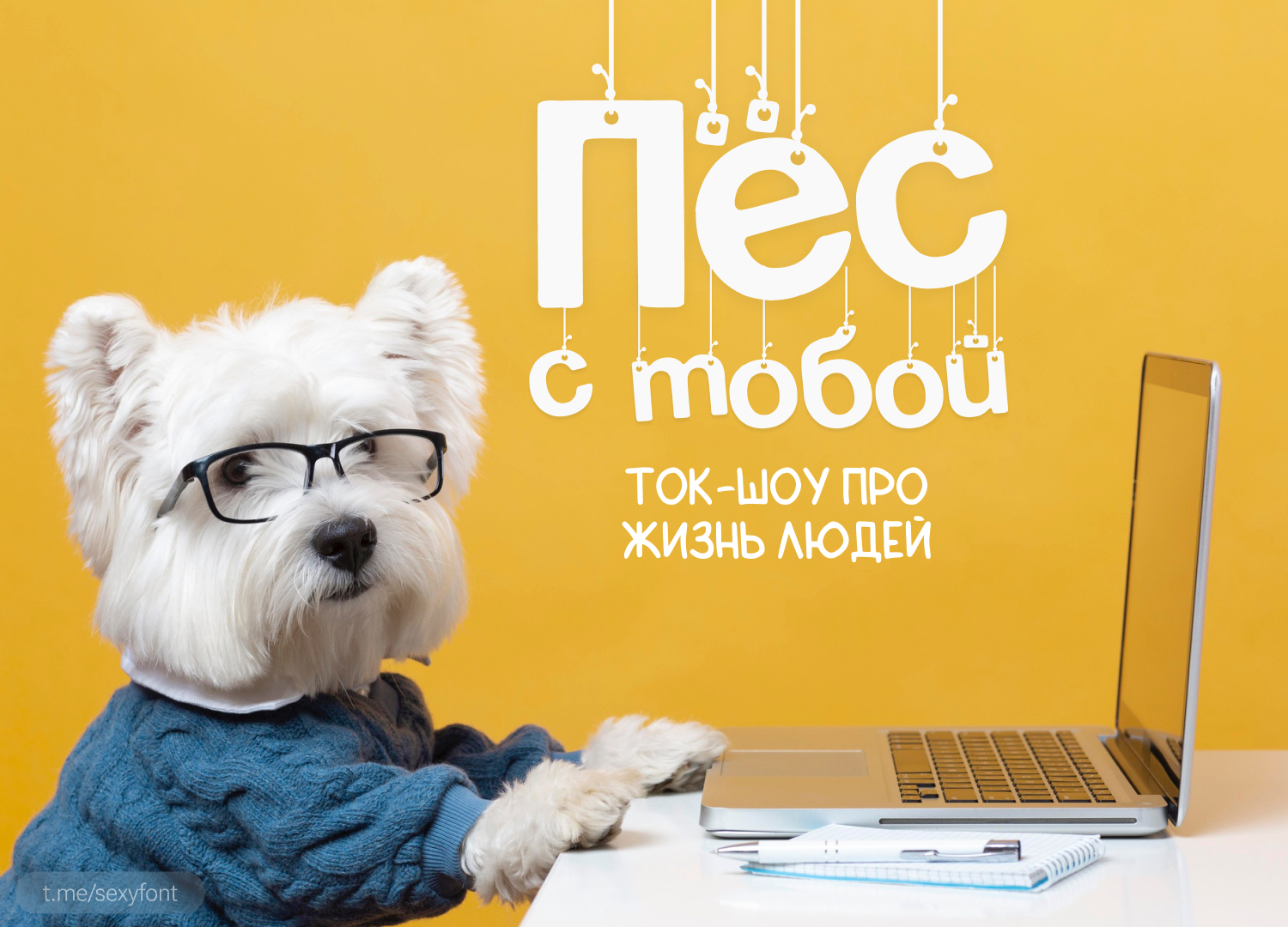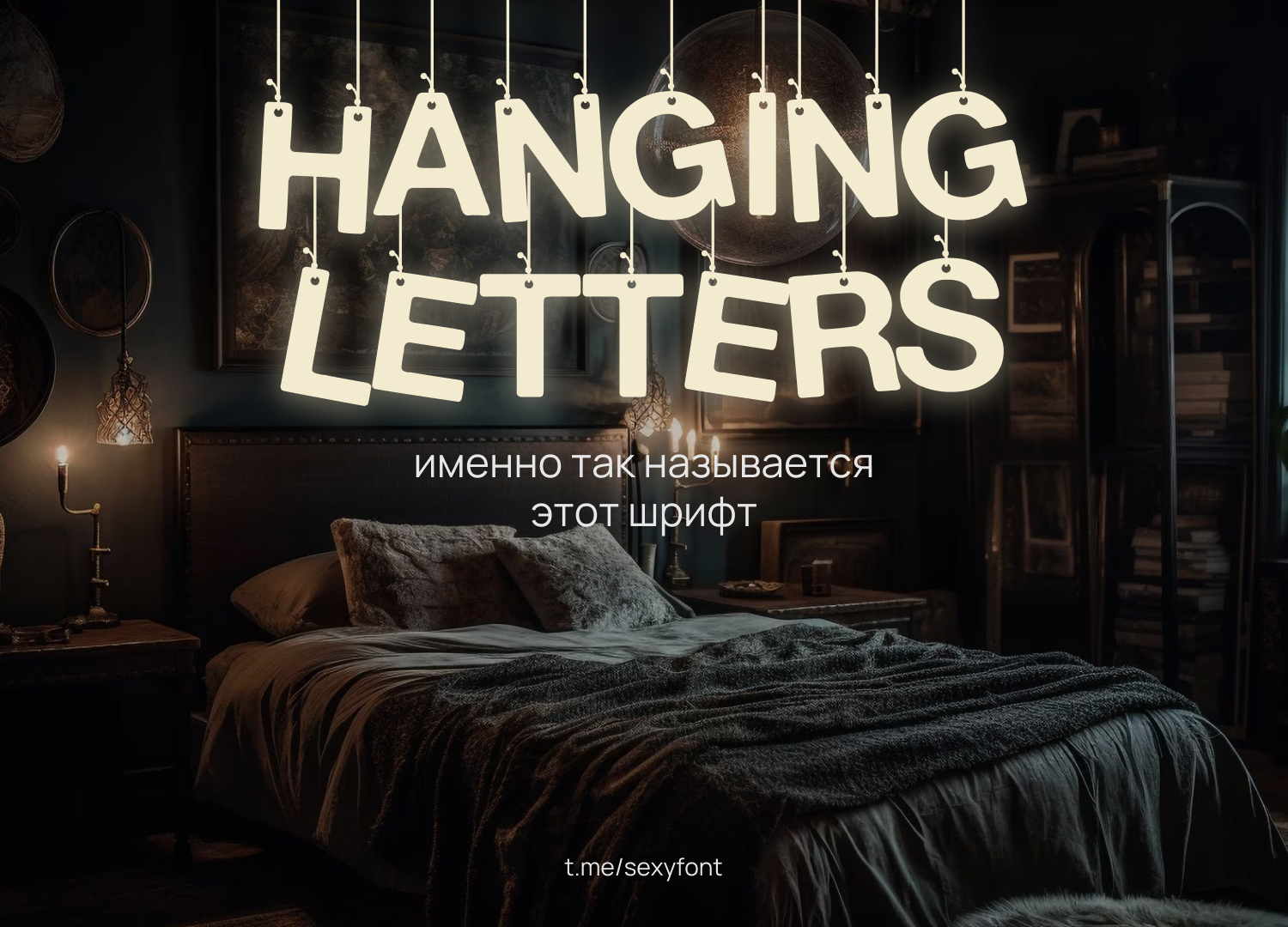
Шрифт на веревочках
Очень старенький, возможно вы его встречали ранее, но не придавали значение. Все из-за отсутствия нормальной презентации. Постарался исправить это дело. Автор: Индийский дизайнер Hareesh Seela. Бесплатно для личного использования. Для коммерции просят скинуть автору донат. Не знаю как вы это сделаете в Индию)